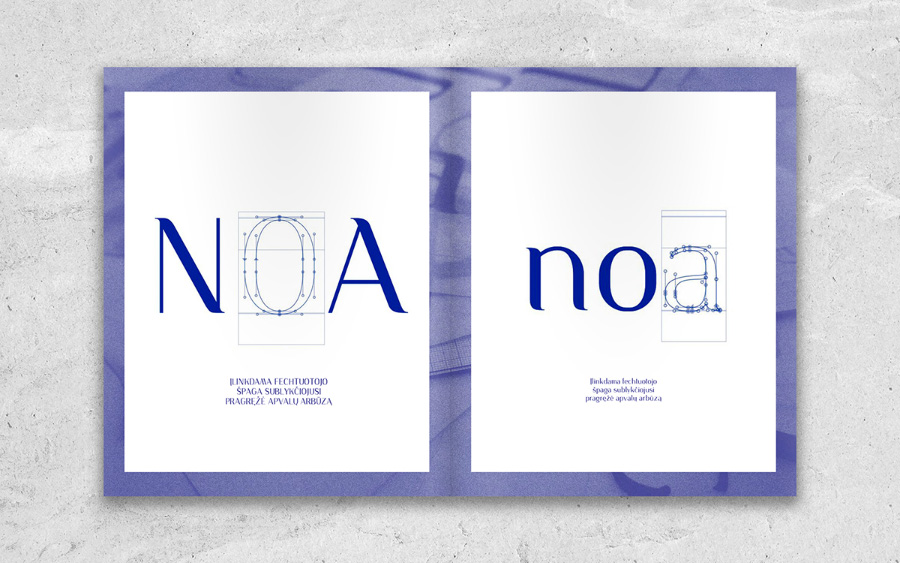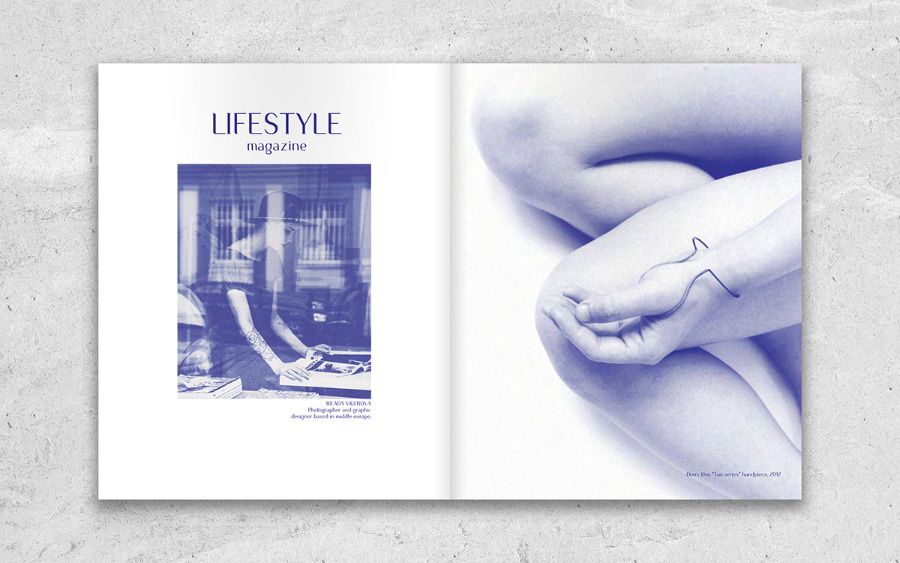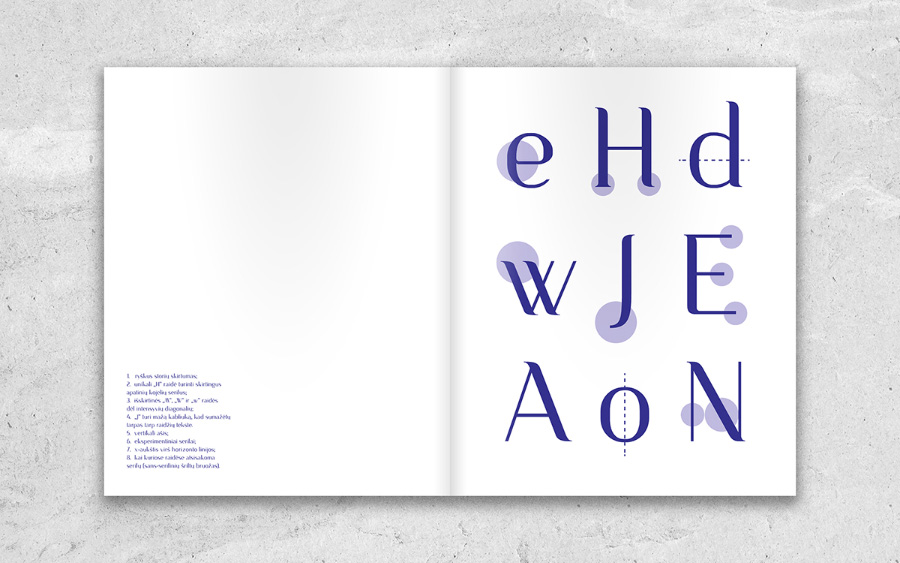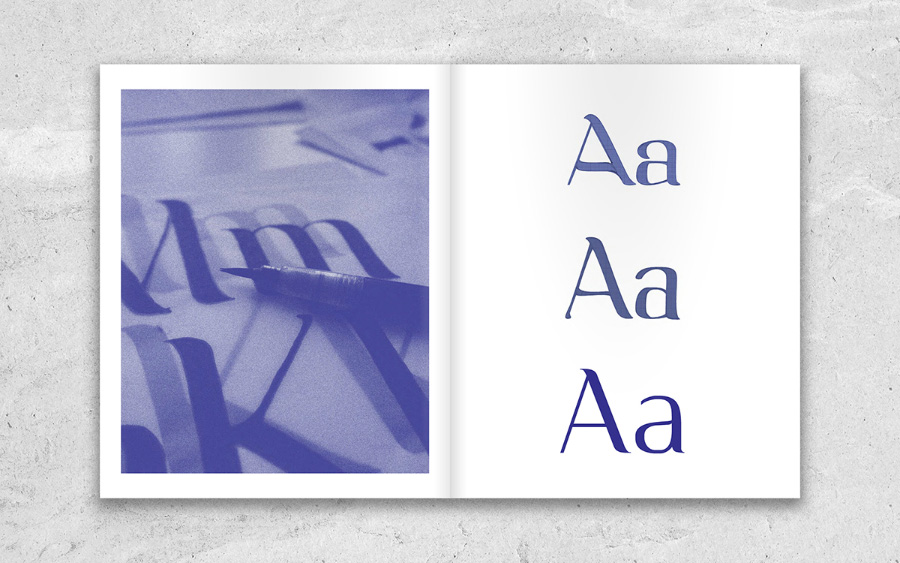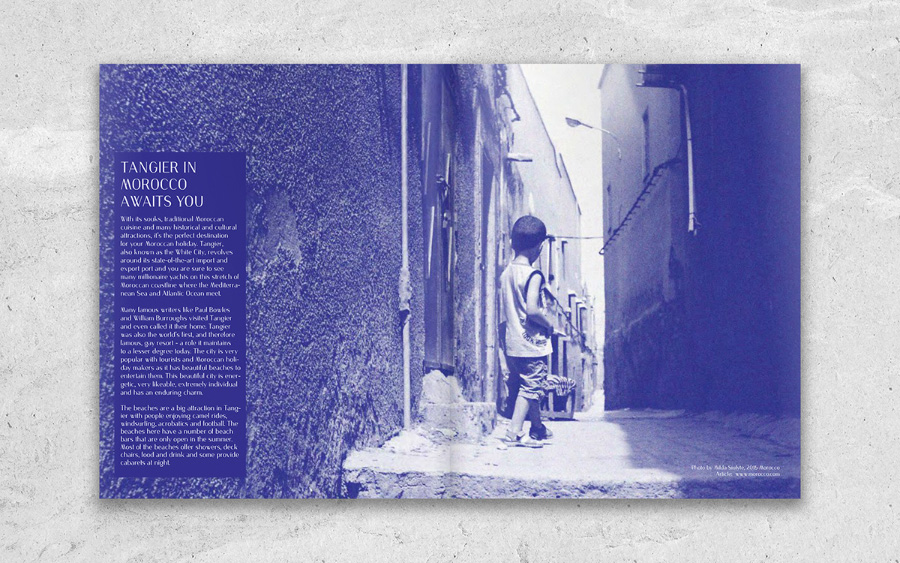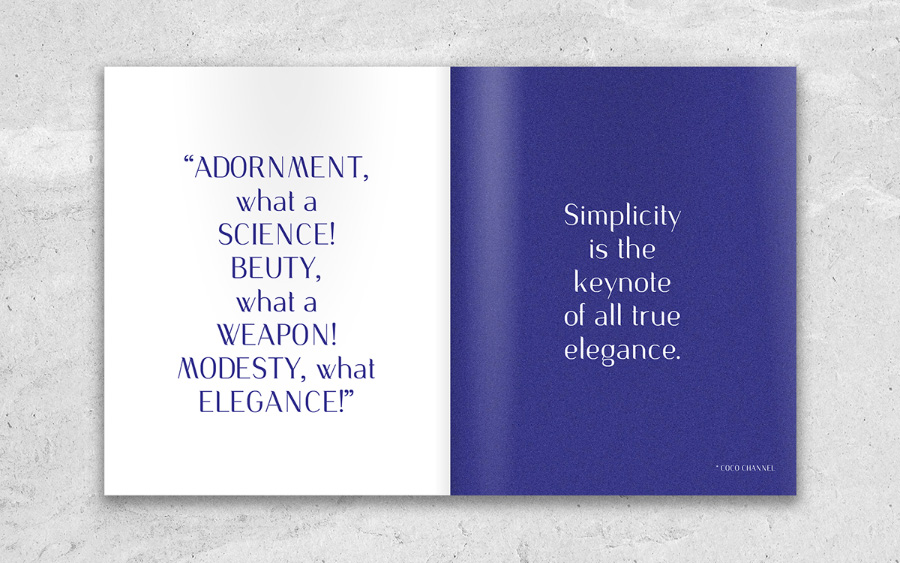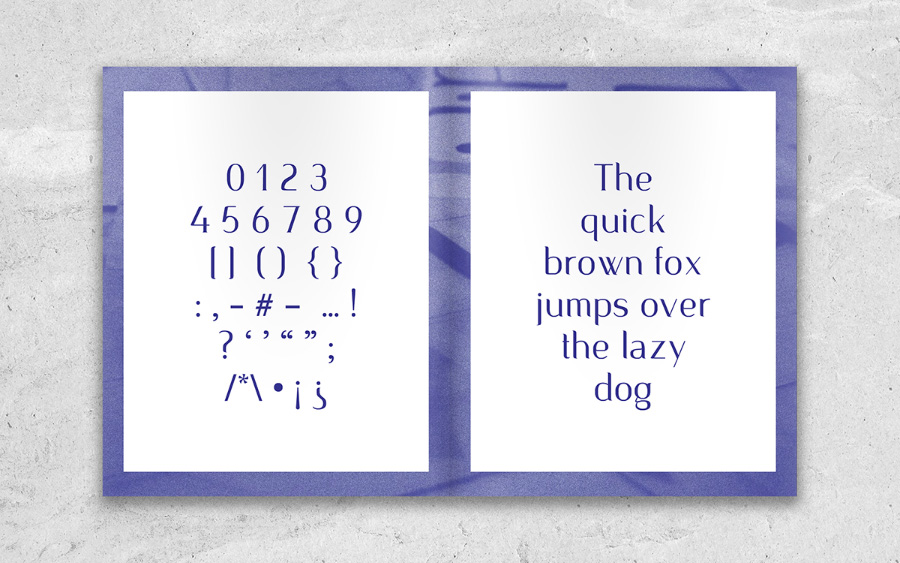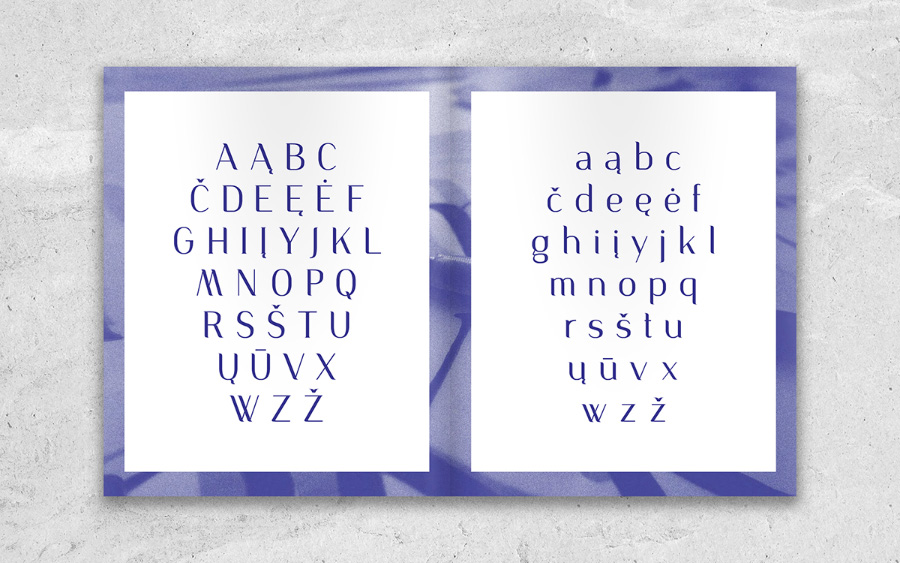
米尔达定期免费字体
Milda Regular Free Typeface
Milda Regular Free字体是来自“Rotis”和“Didot”灵感的半衬线现代字体。米尔达将给你的设计优雅,简单和女性化的触摸。因此,这种字体对于时尚或生活方式的杂志,海报或数字用途来说是非常好的。所以,现在下载,成为关注的中心!